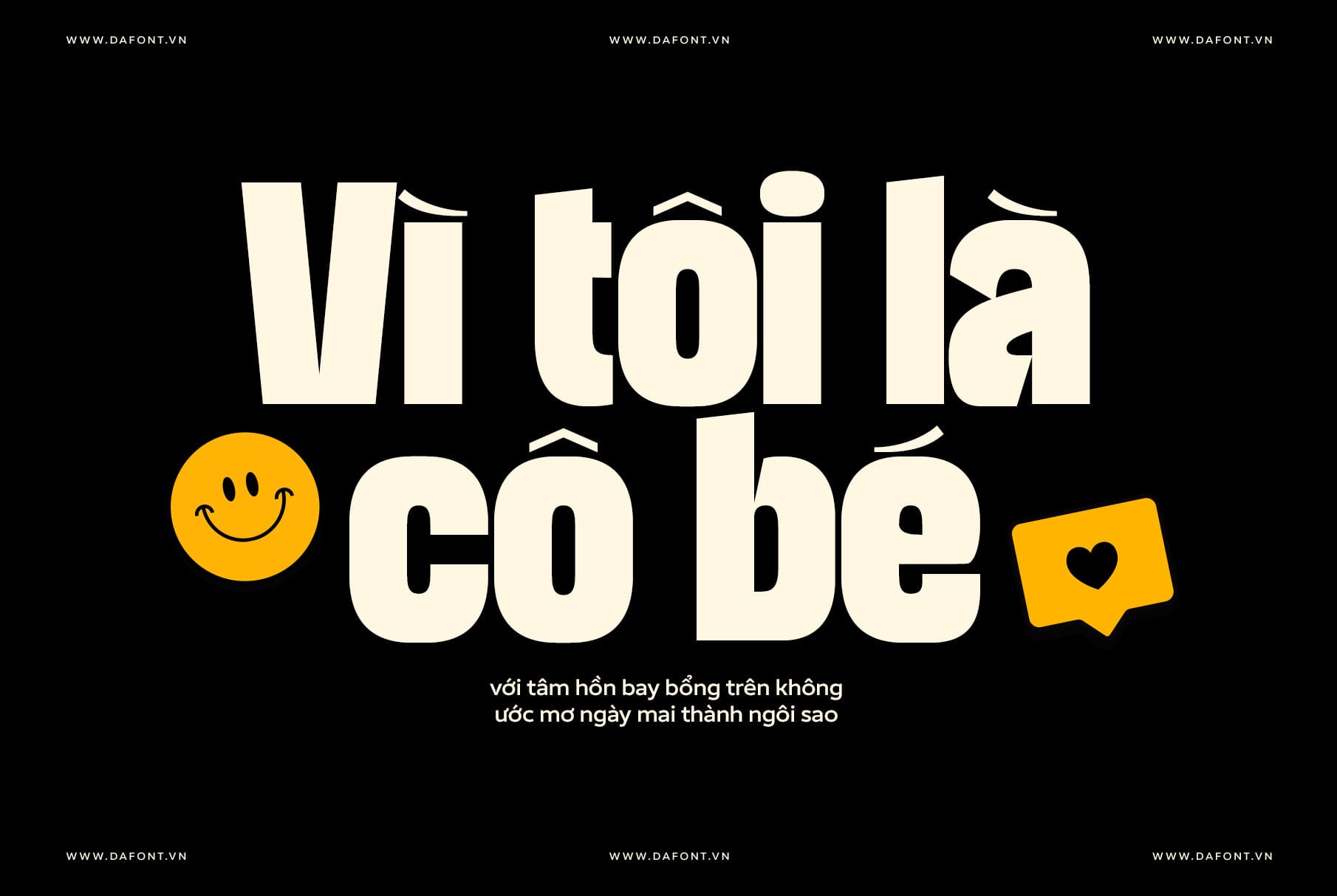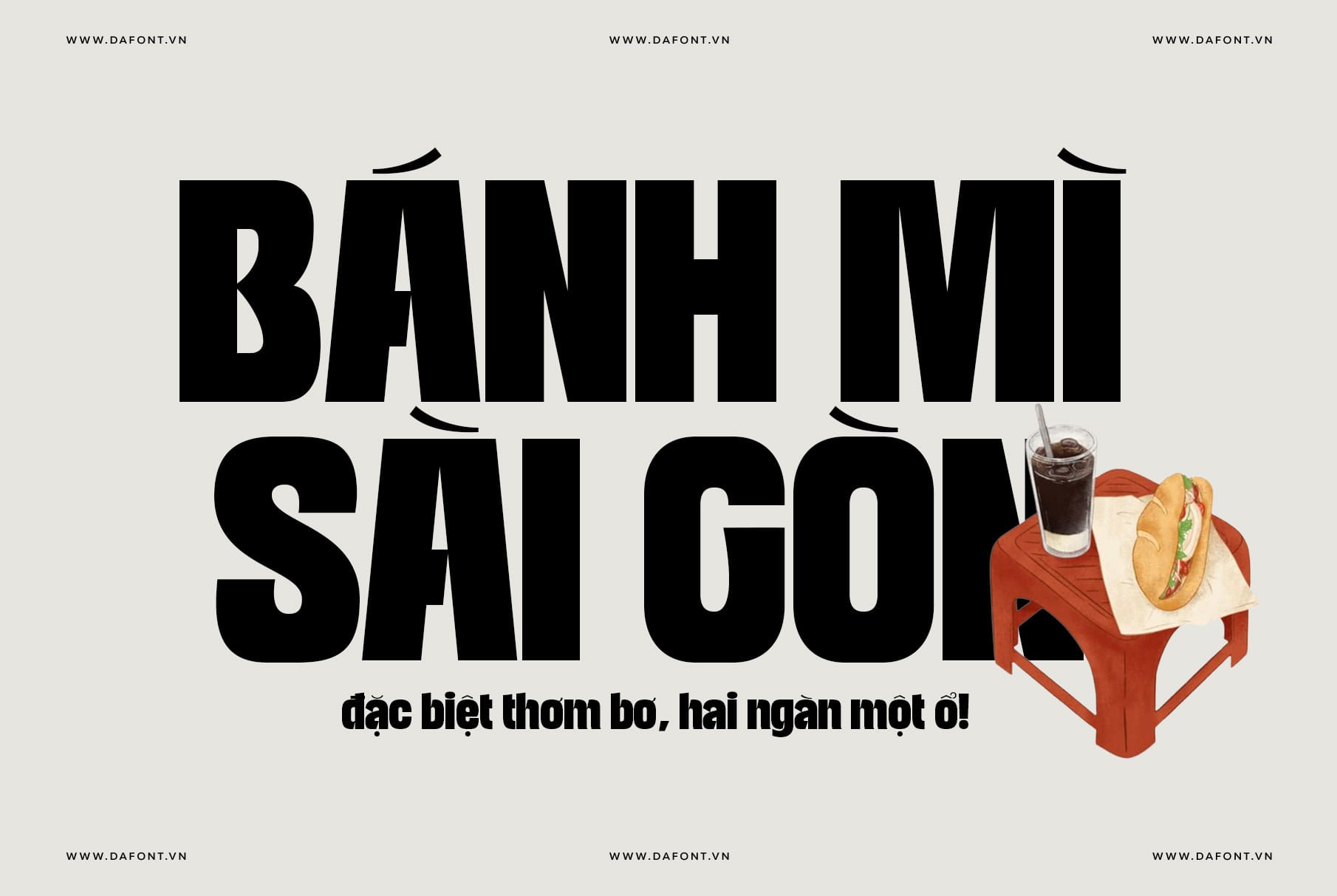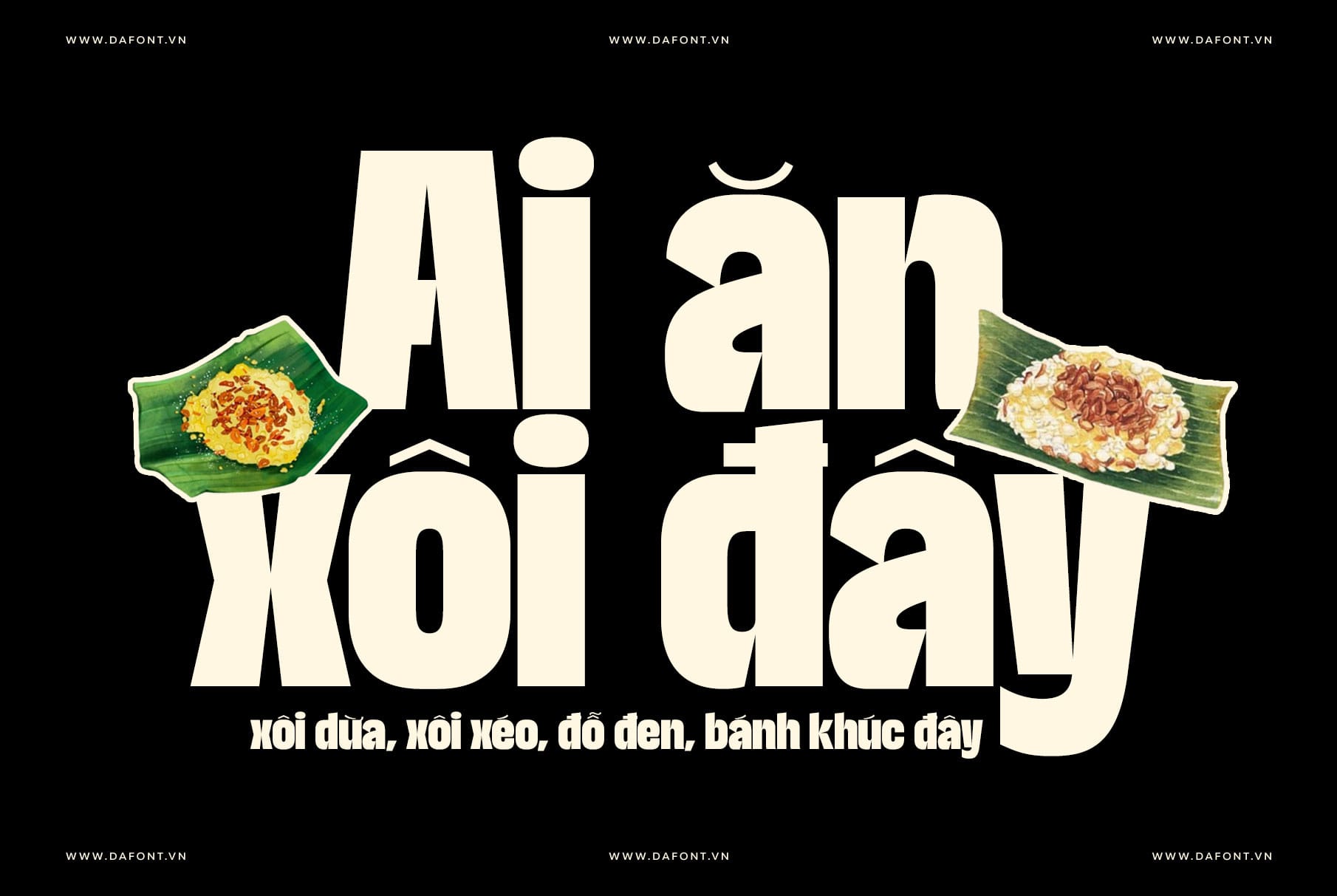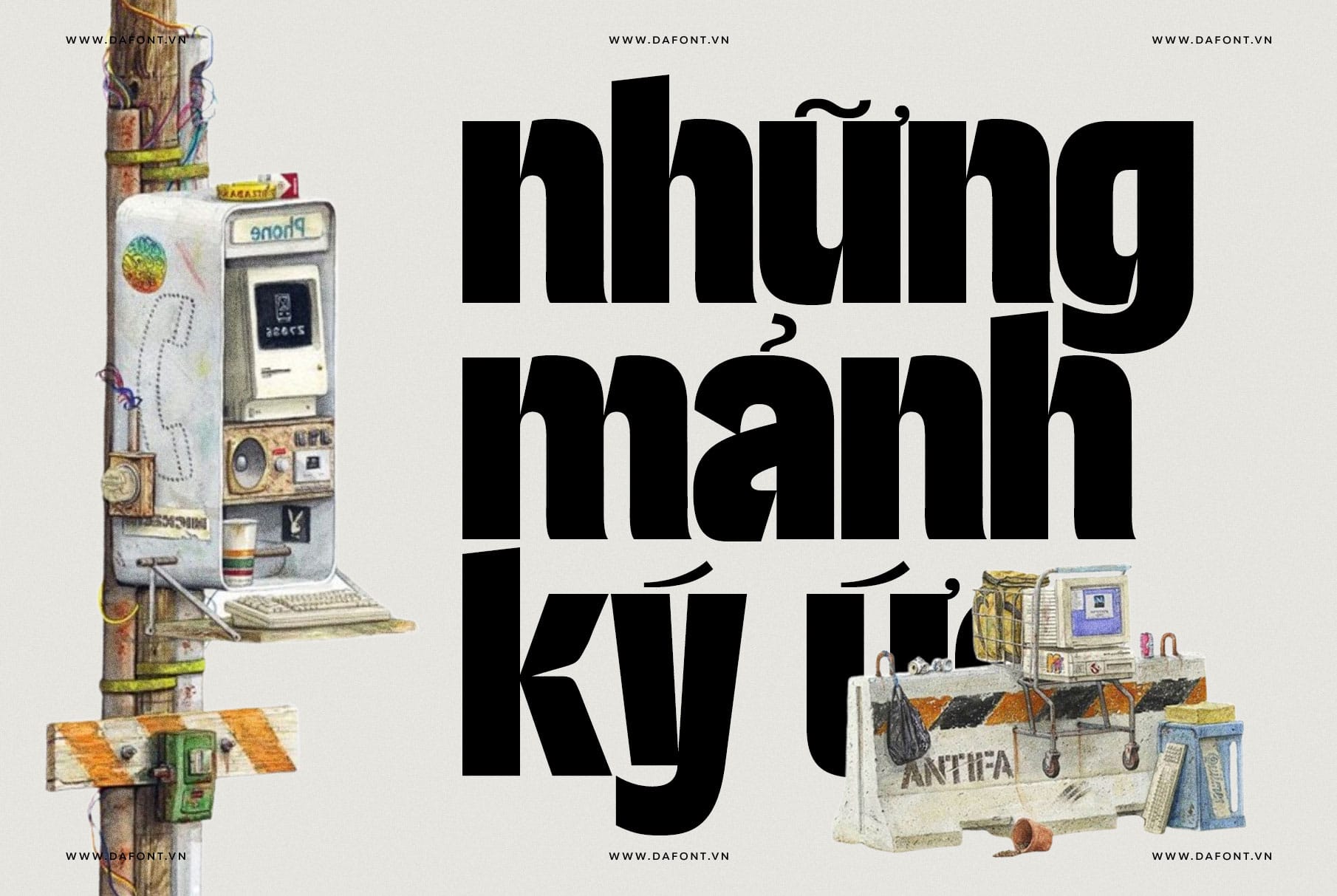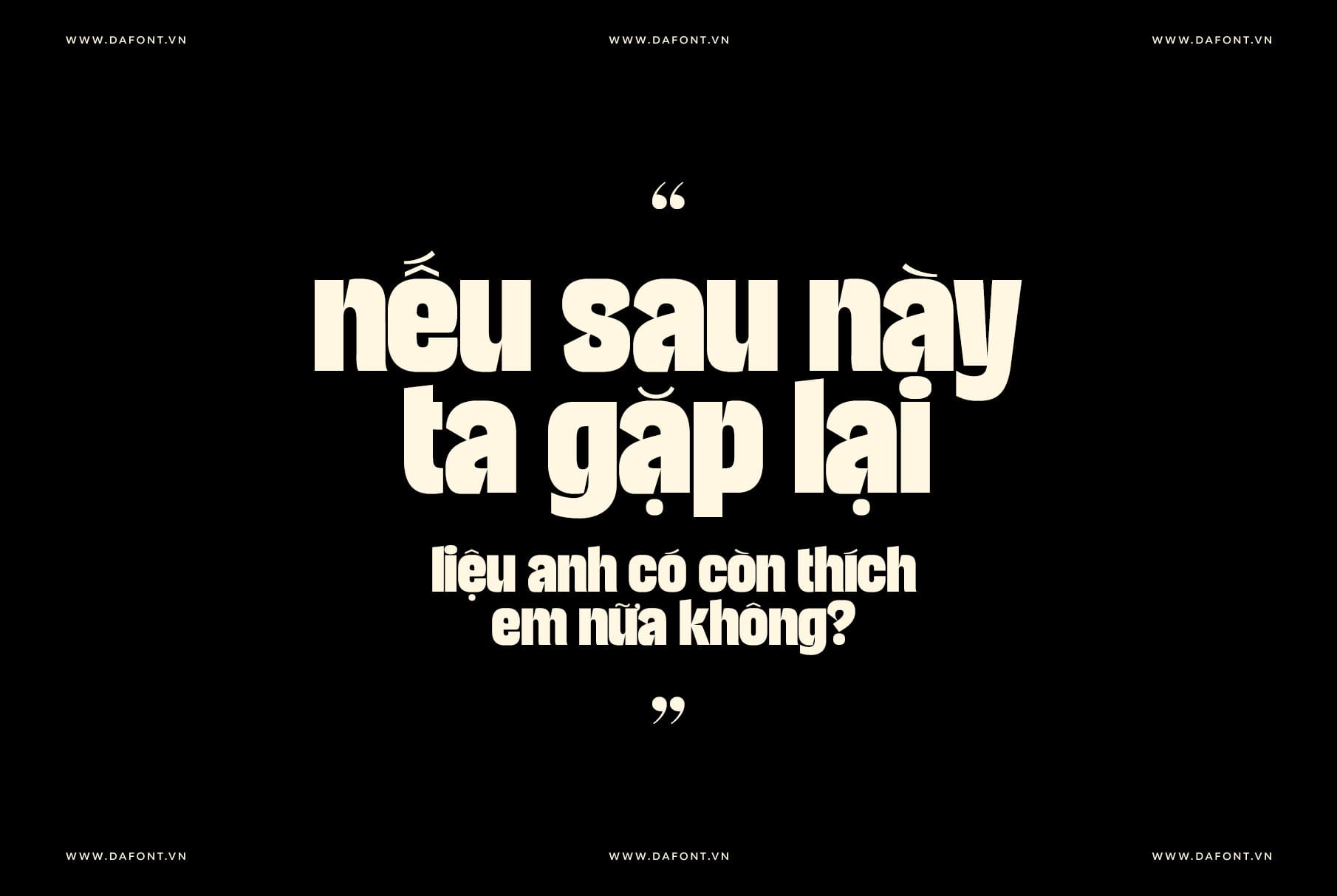
DFVN TAN – KULTURE
Kiểu chữ đậm nét mang phong cách retro
Bạn đang tìm kiếm một font chữ nổi bật để nâng tầm thiết kế của mình? DFVN TAN – KULTURE chính là lựa chọn hoàn hảo! Đây là một font chữ hiển thị (display font) với thiết kế đậm nét, mang phong cách retro đầy cá tính
DFVN TAN – KULTURE – Với phong cách hoài cổ
TAN – KULTURE là một kiểu chữ display typeface, được thiết kế để gây ấn tượng mạnh mẽ trong các dự án sáng tạo như tiêu đề, logo, poster hay banner. Với cảm hứng từ phong cách cổ điển thập niên 70, font này kết hợp giữa nét hoài cổ và sự đơn giản hiện đại, tạo nên một diện mạo vừa độc đáo vừa dễ sử dụng.
Đặc điểm nổi bật của TAN – KULTURE
DFVN TAN – KULTURE không chỉ đẹp mà còn sở hữu những đặc trưng riêng biệt, khiến nó nổi bật giữa vô vàn font chữ khác:
Thiết kế đậm nét, đơn giản nhưng hiệu quả
Các ký tự của TAN – KULTURE được tạo nên bởi những đường nét dày dặn, mạnh mẽ, mang lại cảm giác chắc chắn nhưng không rườm rà. Sự tối giản này giúp font dễ dàng hòa hợp với nhiều phong cách thiết kế.
Khoảng cách chữ chặt chẽ (Tight kerning)
Khoảng cách giữa các ký tự được điều chỉnh kỹ lưỡng, tạo nên sự liền mạch và chuyên nghiệp. Đây là điểm cộng lớn khi sử dụng font trong các thiết kế cần sự tập trung cao như tiêu đề hay áp phích.
Hơi hướng retro cổ điển
TAN – KULTURE mang đậm chất vintage, gợi nhớ đến những thiết kế hoài cổ. Điều này khiến nó trở thành lựa chọn lý tưởng cho các dự án muốn tái hiện phong cách xưa cũ nhưng vẫn giữ được nét hiện đại.
Ứng dụng của DFVN TAN – KULTURE trong thiết kế
TAN – KULTURE không chỉ là một font chữ đẹp mà còn rất linh hoạt. Dưới đây là một số ý tưởng ứng dụng:
• Thiết kế Logo: Được thiết kế đậm nét và phong cách retro giúp logo của bạn dễ nhận diện và tạo ấn tượng lâu dài.
• Tiêu đề và poster: Khi sử dụng ở kích thước lớn, TAN – KULTURE ngay lập tức thu hút sự chú ý, rất phù hợp cho các chiến dịch quảng cáo.
• Sản phẩm in ấn: Từ danh thiếp, tạp chí đến bao bì, font này mang lại sự độc đáo và chuyên nghiệp.
• Thiết kế web: Sử dụng DFVN TAN – KULTURE cho các tiêu đề hoặc điểm nhấn trên website để tạo sự khác biệt so với đối thủ.
DFVN TAN – KULTURE: Lựa chọn của sự độc đáo
Điều gì làm nên sức hút của DFVN TAN – KULTURE? Đó là cá tính riêng biệt, khả năng giúp bạn khẳng định dấu ấn trong từng thiết kế. Không đại trà, không nhàm chán.